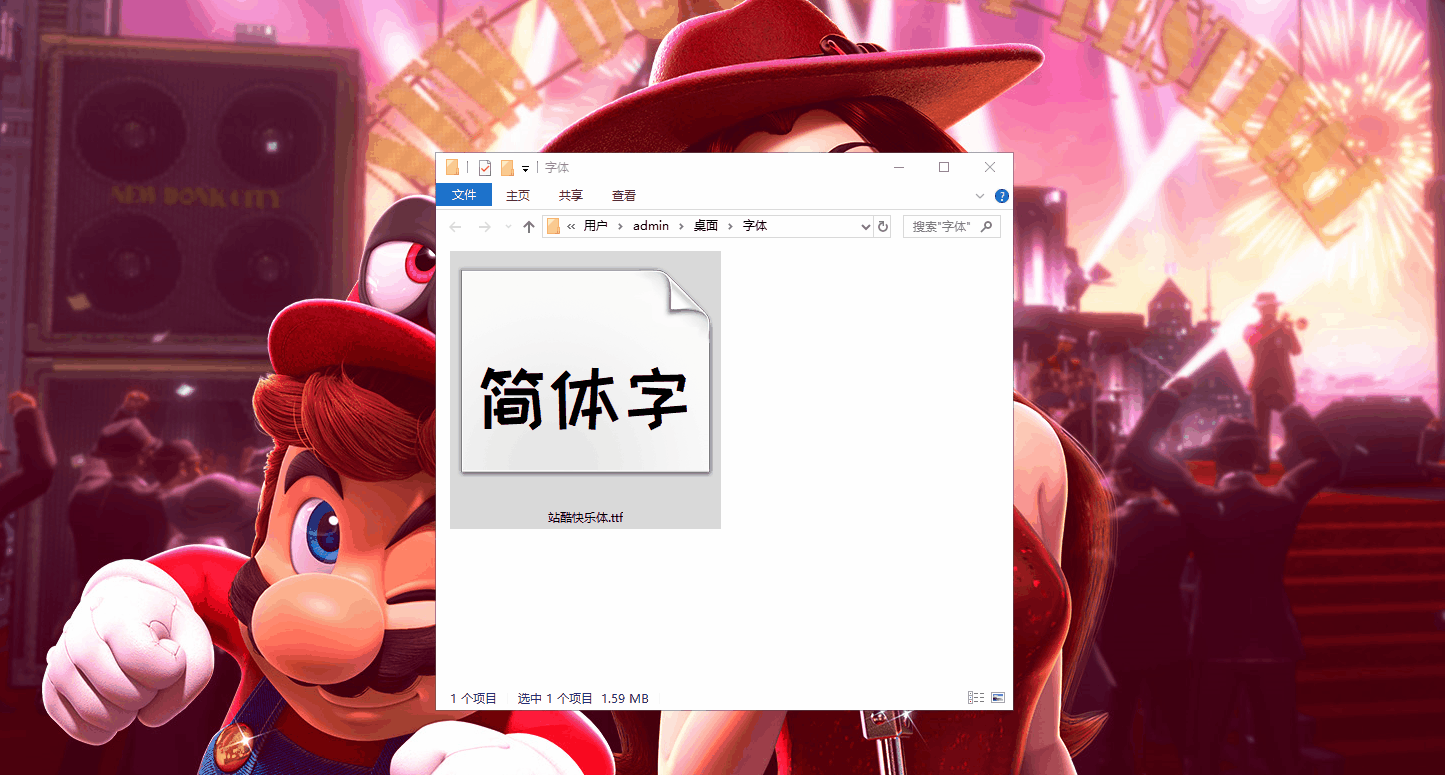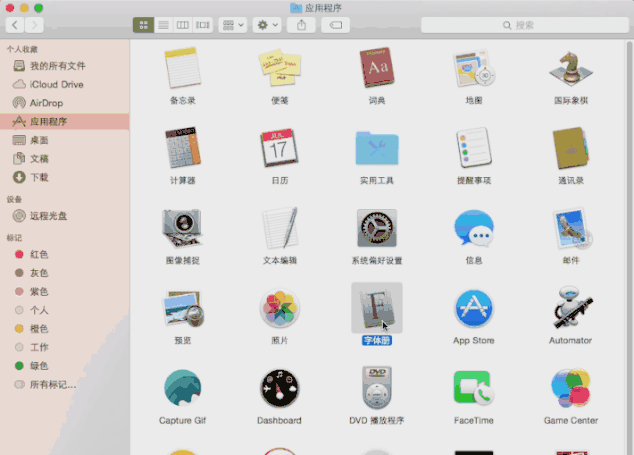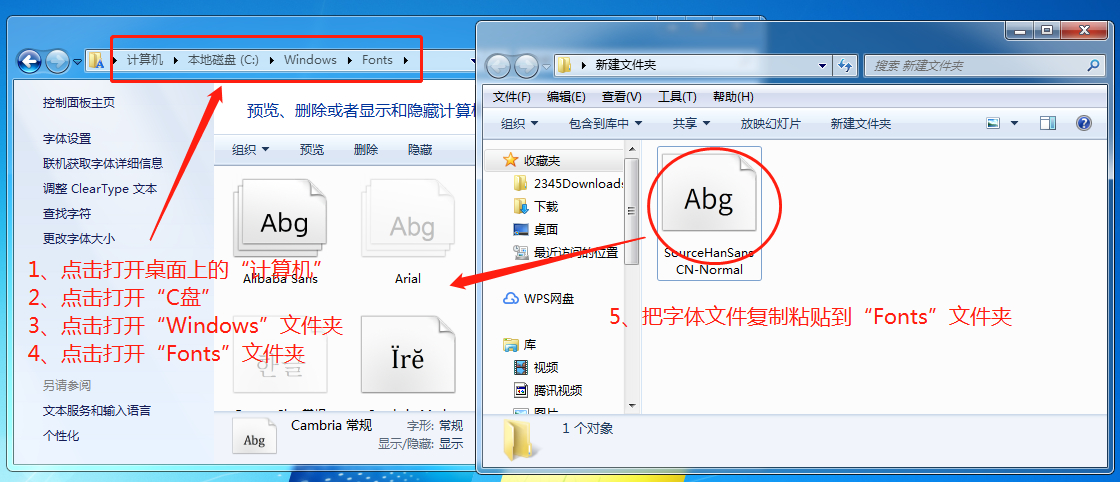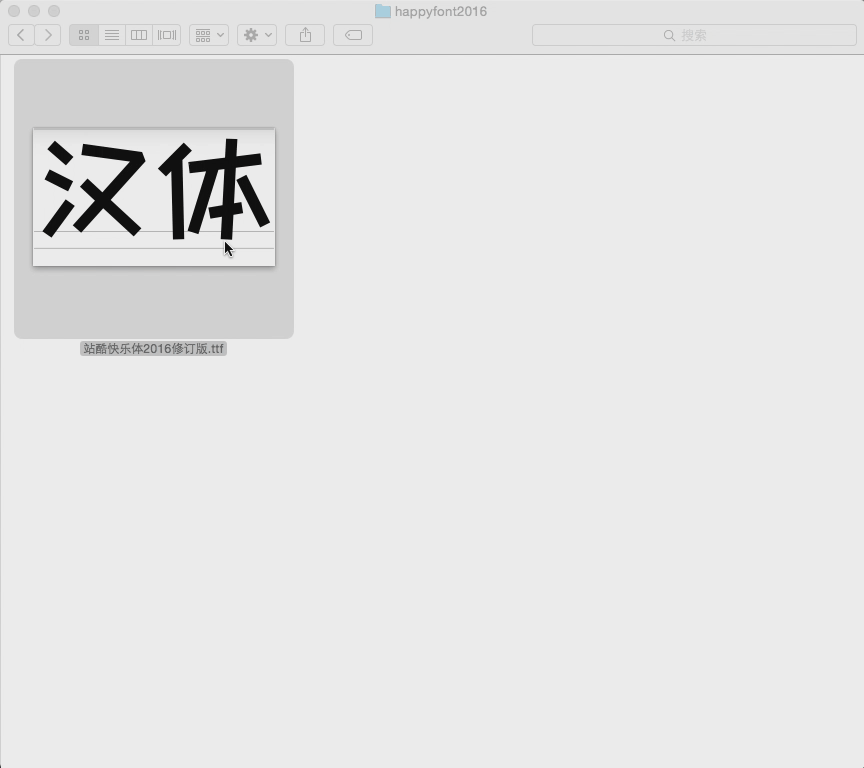
字重是什么:字重可以理解为字体粗细,一般用于描述同一家族字体里不同笔画粗细的字体,例如:Thin、Light、Regular、Medium、Bold、Heavy、Black。
衬线字体与无衬线字体:现在西方国家字母体系分为两类:衬线字体(serif)以及无衬线体(sans serif)
衬线字体:在字的笔画开始、结束的地方有额外的装饰,而且笔画的粗细会有所不同,更强调于一个单词,因此易读性比较高,易于换行,有助于减少阅读错误,中文字体中的宋体就是一种标准的衬线字体,适用于正文等需要易于阅读和识别性的场合。
无衬线字体:这种字体的字母没有额外的装饰,而且笔画的粗细差不多,通常具有相同的曲率和笔直的线条,强调每一个字母,因此比较醒目,更现代、简约、清新,具有艺术感,无衬线字体与中文字体中的黑体相对应,适用于标题等需要醒目但不需长时间阅读的场合。
GB18030和GB2312字符集的区别:GB2312是GB2312-1980的简称,总共包含6763个中文简体字符,几乎可以满足基本的汉字使用需求,GB2312是目前大陆用的最多的中文字符集。GB18030字符集是GB18030-2000字符集的简称,GB18030字符集包含27533个中文字符,除了常用的简体,还包含了中文繁体。